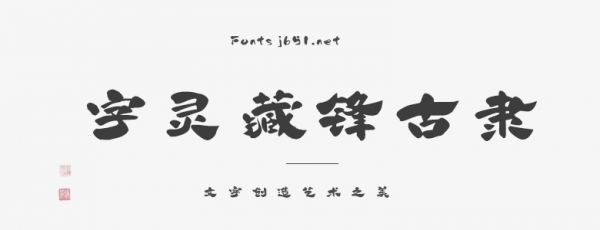
字灵藏锋古隶 大小:5.6MB 分类:其它中文 环境:Windows 更新:2024-02-01 下载 热门排行 JOJO奇幻冒险 蜡笔小新 咒语旅团 越狱模拟器 最后生还者 架空地图 交易猫 乐高大乱斗 小偷模拟器 石河伦吾的朋友们 道友请留步 欢乐小镇 简介 字灵藏锋古隶是一款古典优雅的中国风隶书字体,适合应用于艺术设计、各类广告和产品包装设计等领域。 字体使用 使用须知:应官方需求,目前该字体只能通过字由客户端激活才能使用,因此本站提供的是字由客户端安装包 1、下载并安装字由客户端(Mac版、Win版) 2、安装成功后,在软件内搜索“字灵藏锋古隶”,点击即可激活字体(激活字体前会显示绿色圆点)。 3、打开PS、AI等设计软件,框选文本,点击字由里的激活字体,即可使用。